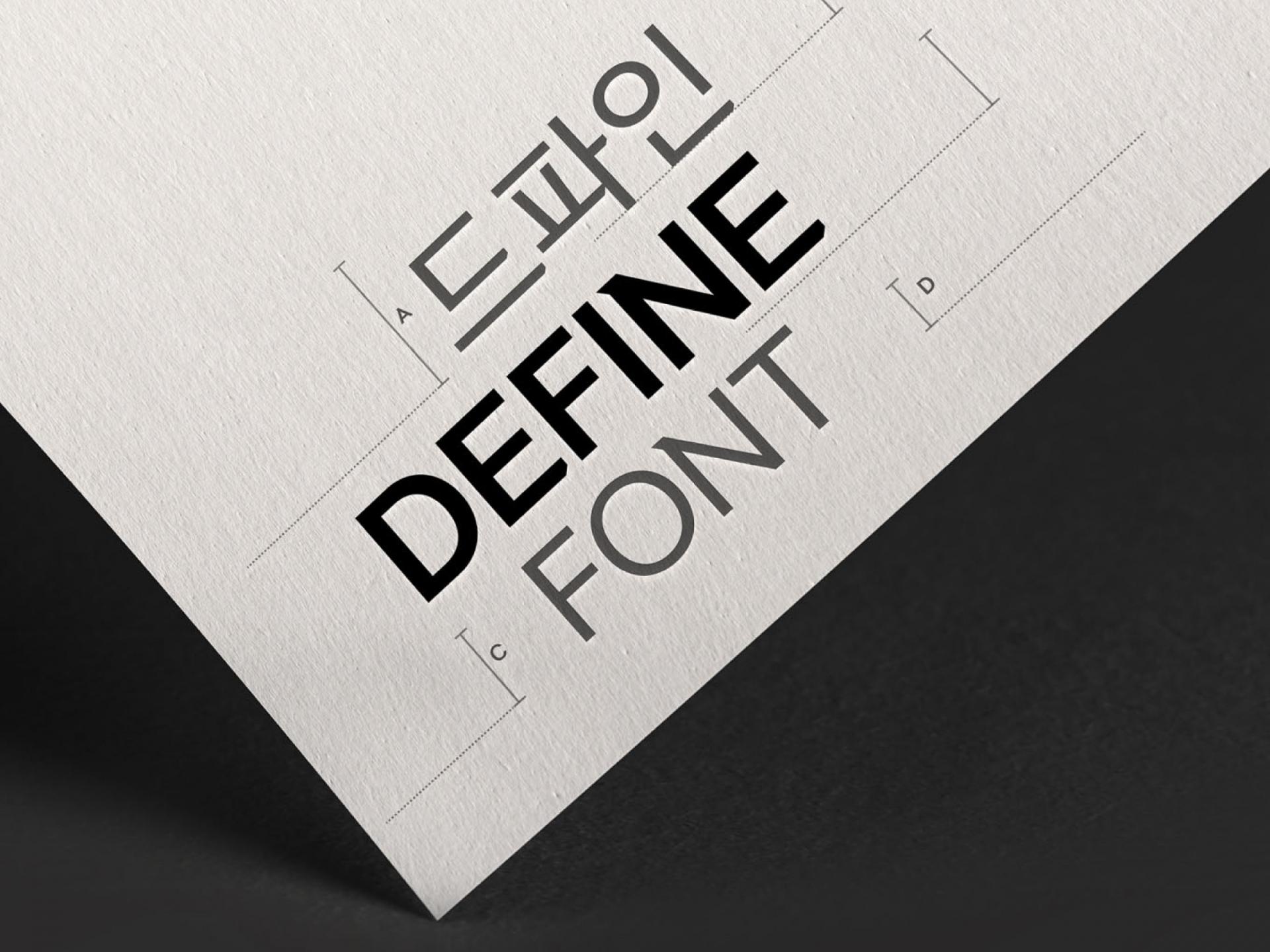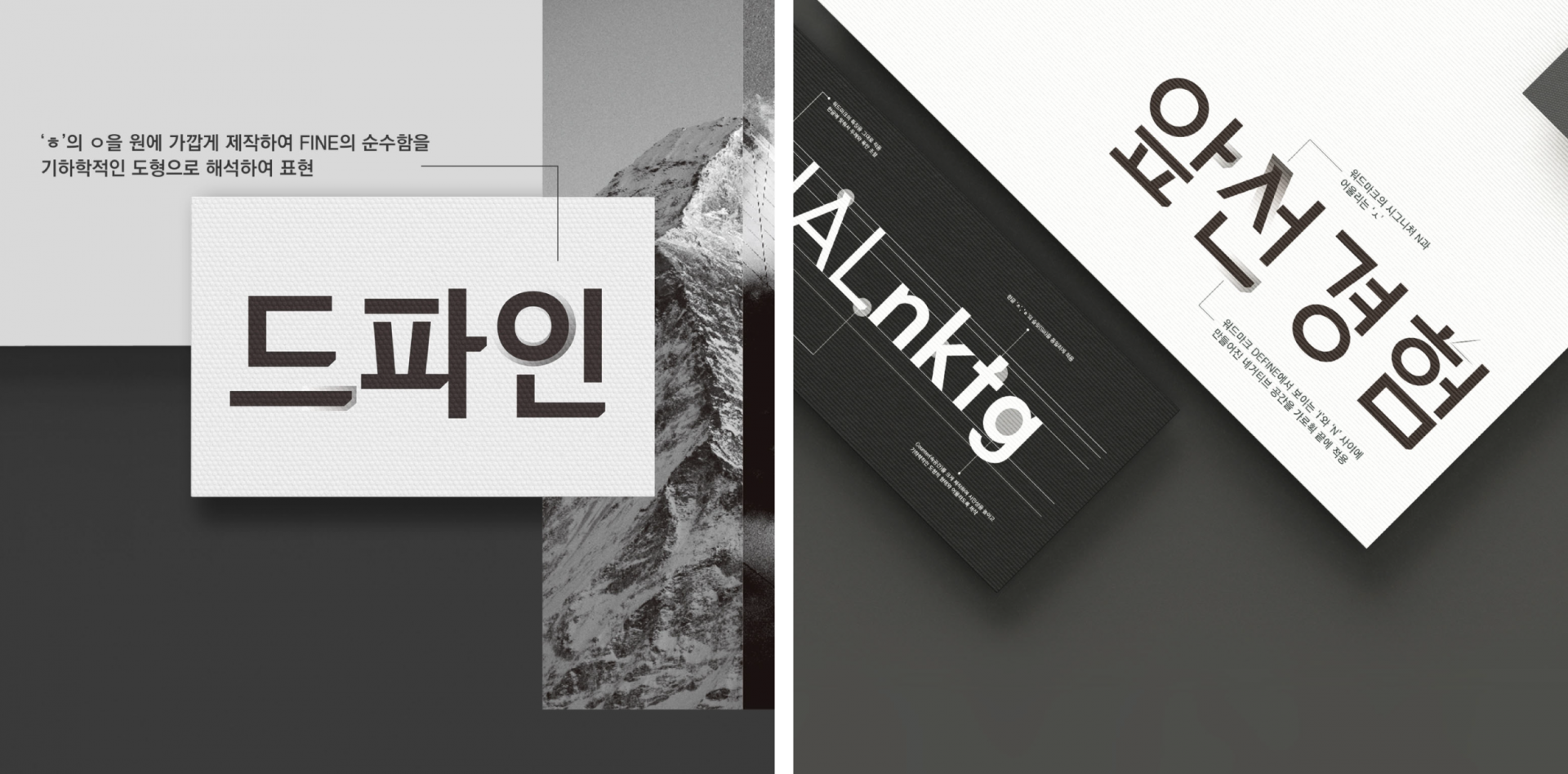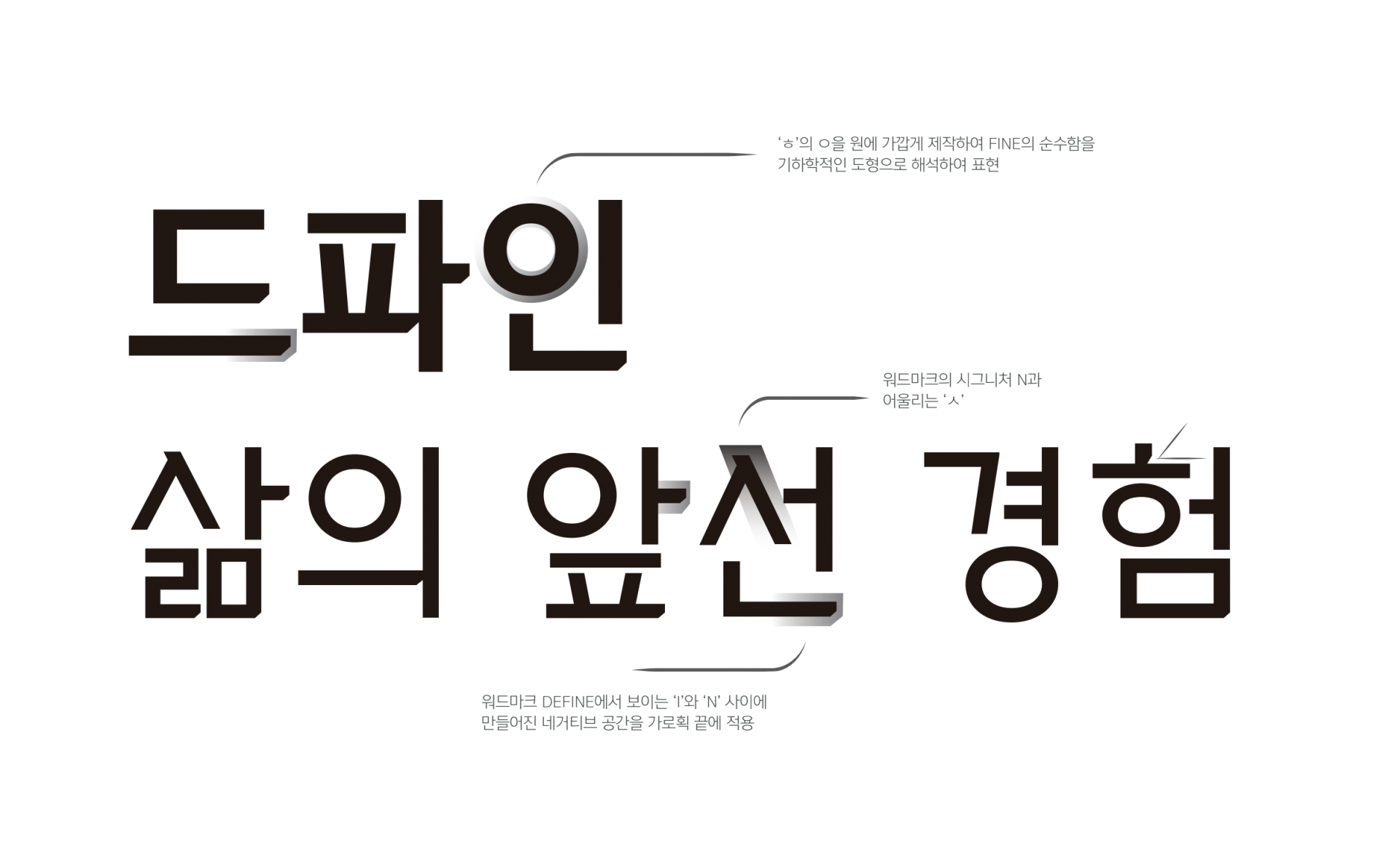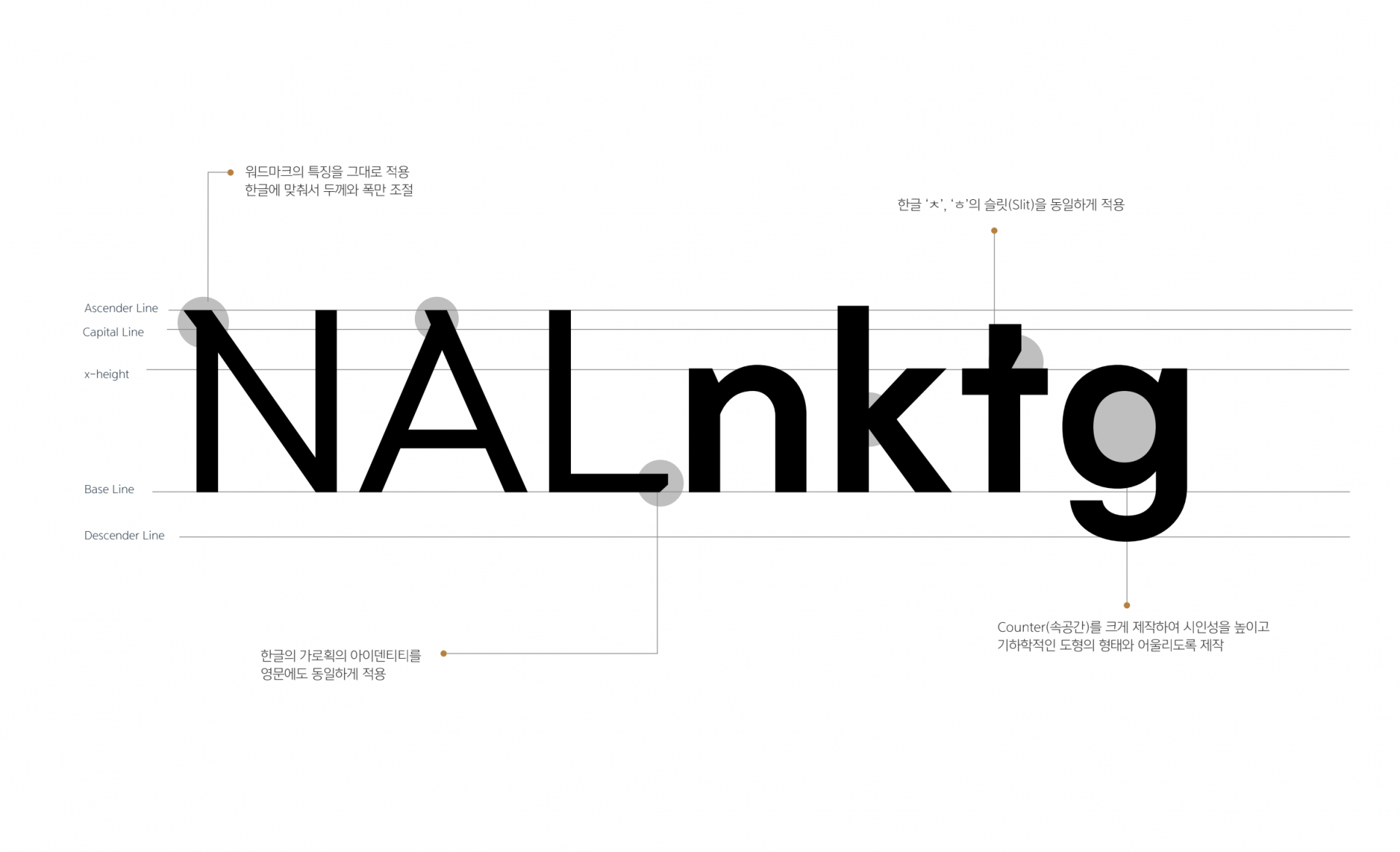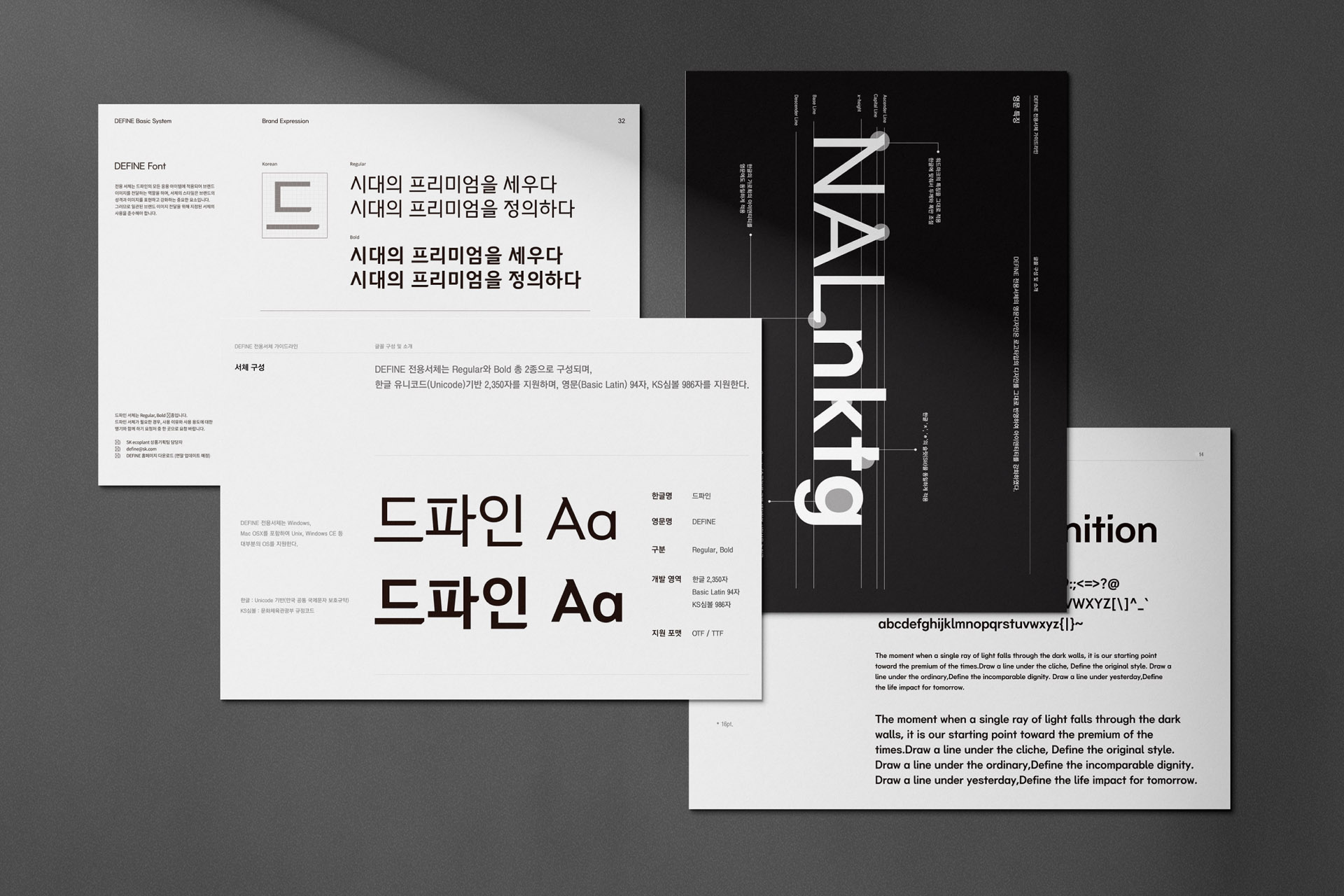
SK에코플랜트 [DEFINE Font]
SK에코플랜트만의 '시대의 프리미엄을 정의'하는 주거 브랜드, 드파인(DEFINE)의 이야기를 효과적으로 표현할 방법으로, 드파인이 정의한 새로운 프리미엄의 기준을 써 내려가기 위해 'DEFINE Font'를 개발했다. 드파인 전용서체는 군더더기 없고 순수하면서 간결함을 강조하는 기하학적인 형태로 제작했다.
포함문자 | 2종 / 한글 2,350자 / 라틴 94자 / KS특수문자 986자 |